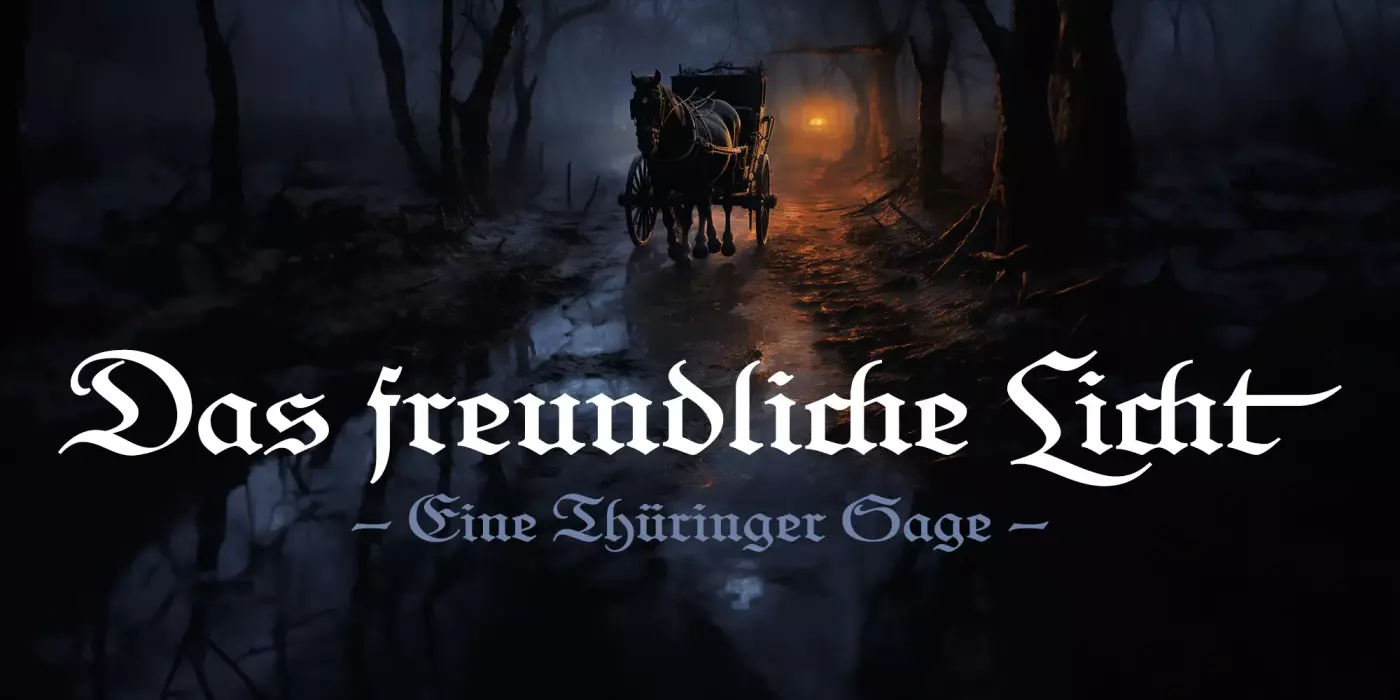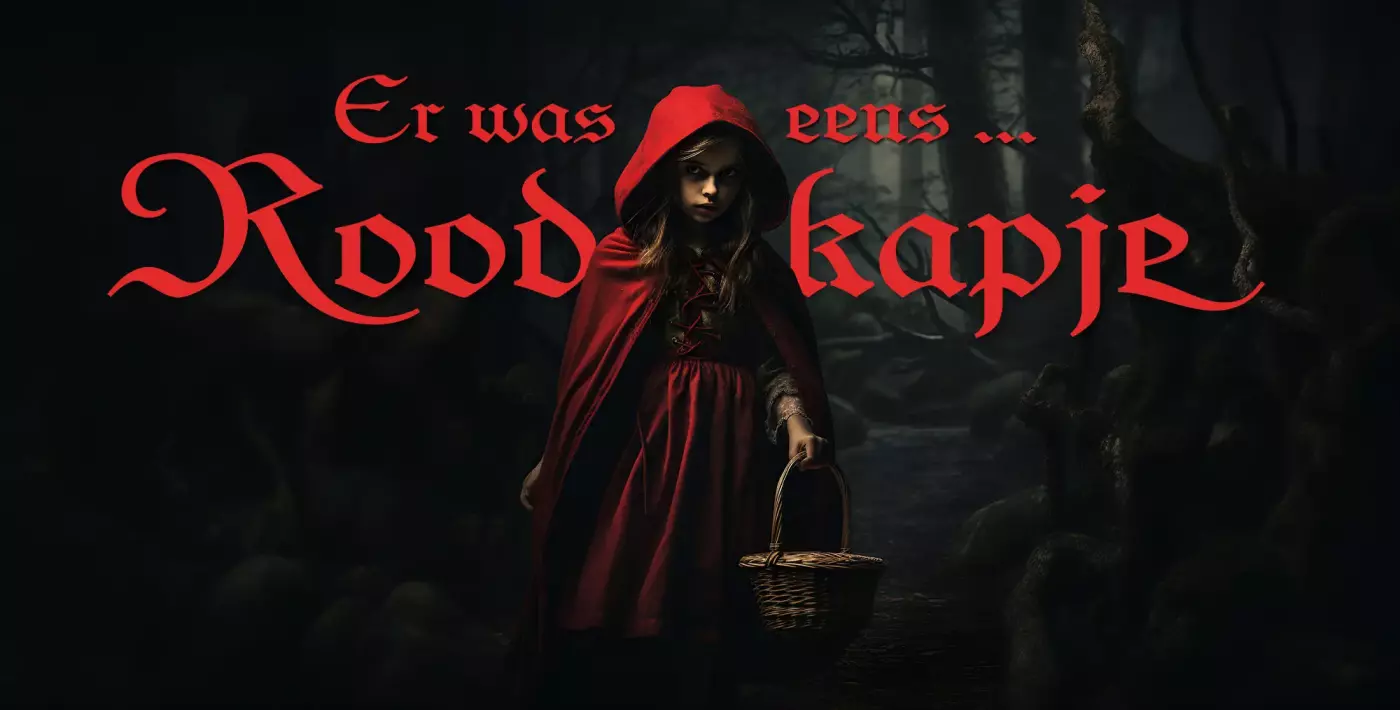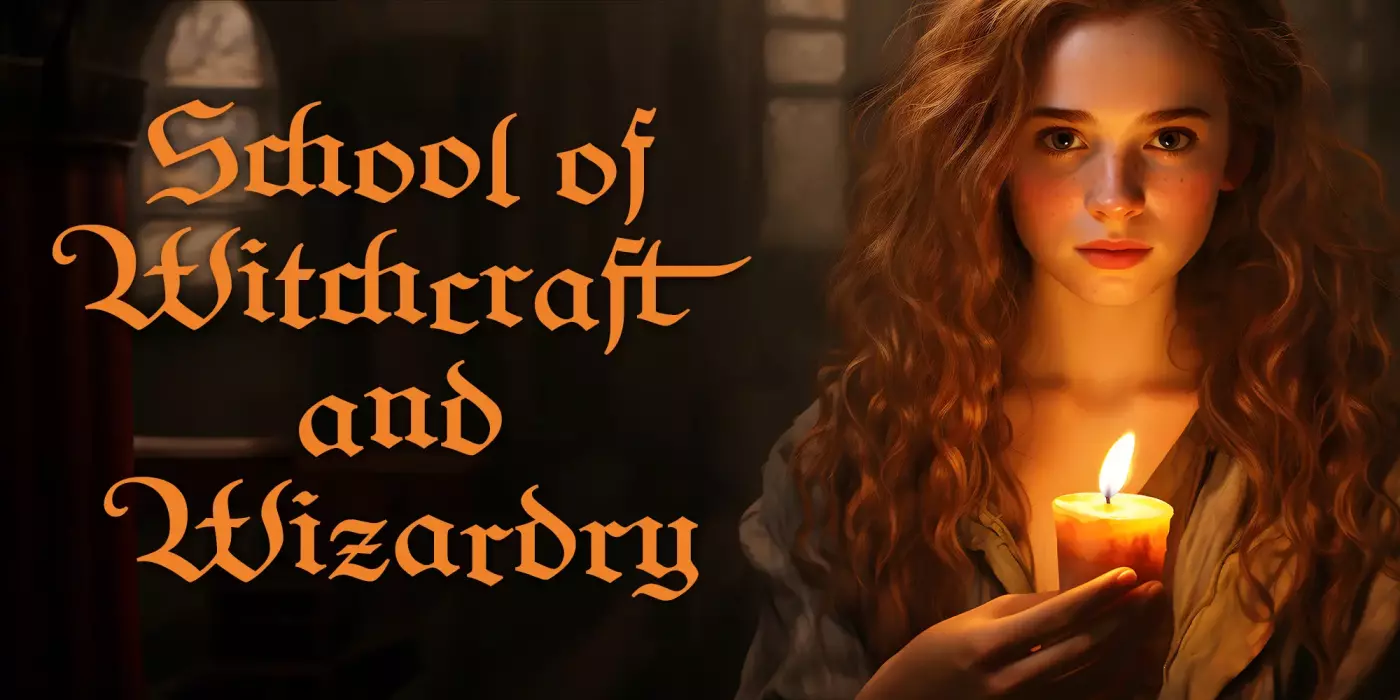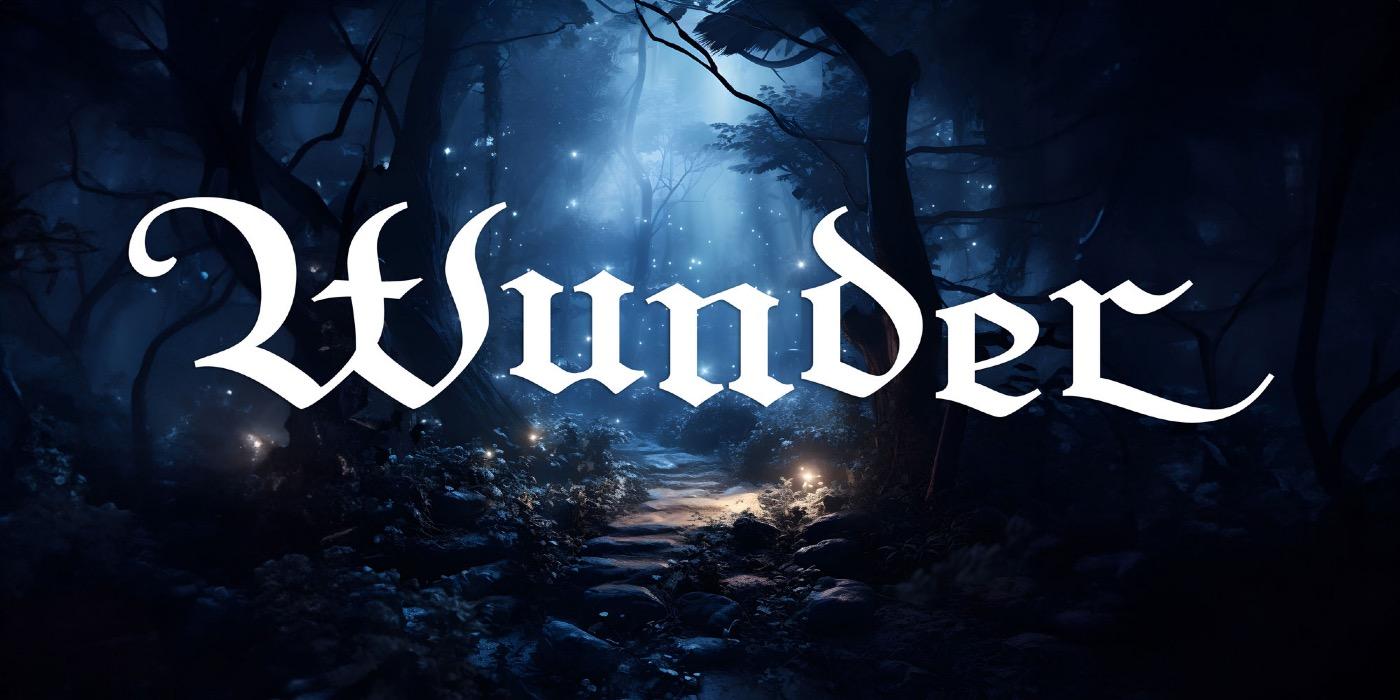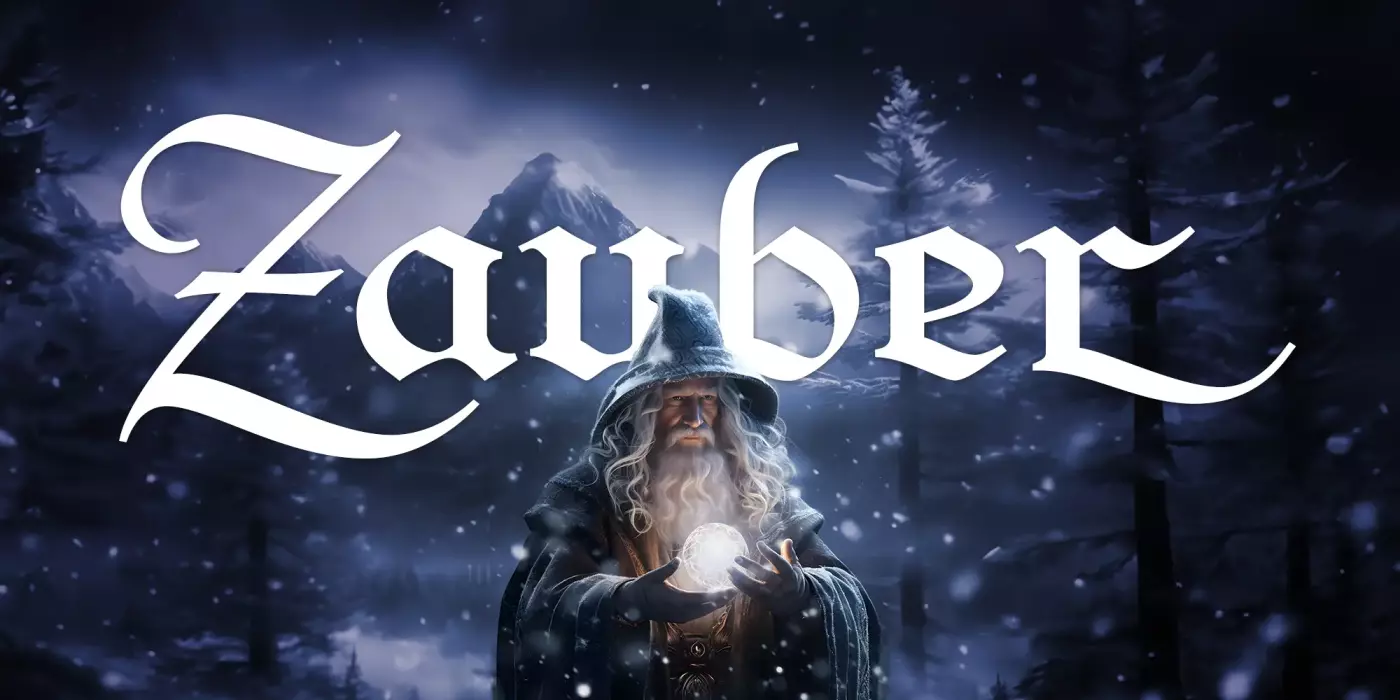
FDI Wunder ist eine Digitalisierung und Erweiterung der Laudahn-Kanzlei auf Basis der Original-Bleisatzlettern. Die Schrift ist in zwei Versionen in westeuropäischer Zeichenbelegung erhältlich: FDI Wunder A basiert auf den Originallettern, während Version B alternative Buchstabenformen im Stile von Antiqua-Schriften enthält.